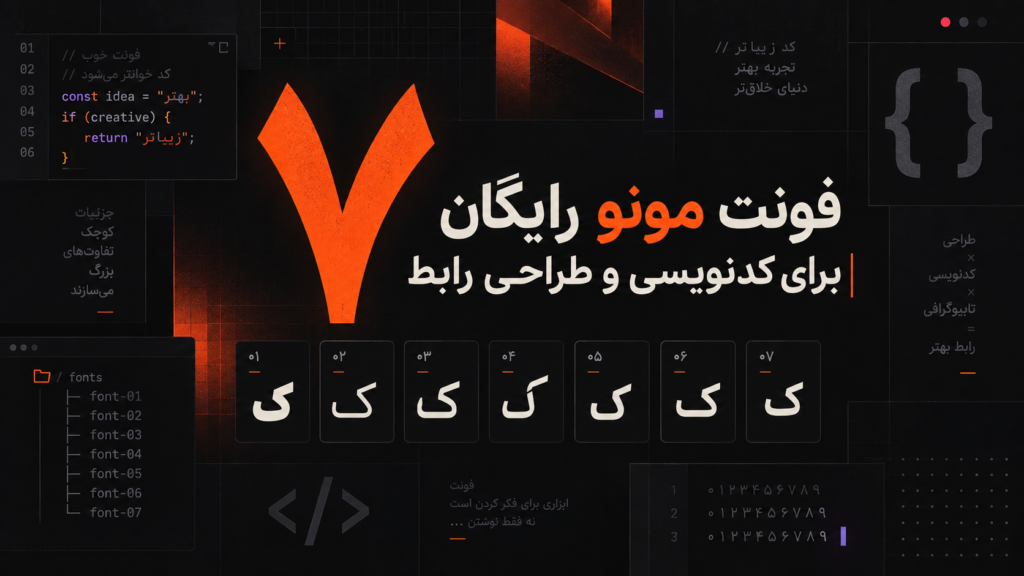
۷ فونت مونو رایگان برای کدنویسی و طراحی رابط
فونت مونو فقط برای نوشتن کد نیست. نظم ثابت حروف در جدول، شماره سفارش، داده‌های مالی و هویت محصولات فنی هم کاربرد دارد. تفاوت اصلی گزینه‌های خوب در تشخیص سریع کاراکترها و خستگی کمتر در استفاده طولانی است.
#چطور این فهرست را انتخاب کردیم؟
تفکیک واضح حروف و اعداد مشابه، تنوع وزن، عملکرد در اندازه کوچک و داشتن شخصیت کافی برای استفاده گرافیکی چهار معیار این فهرست هستند.
#۱. Anonymous Pro
Anonymous Pro فرم آشنا و خوانایی دارد و برای محیط ویرایش کد یا نمونه‌کدهای داخل مقاله انتخابی کم‌حاشیه است.
#۲. Inconsolata
Inconsolata باریک و خوش‌ریتم است؛ در پنجره‌های کدنویسی شلوغ اطلاعات بیشتری را بدون فشردگی آزاردهنده نمایش می‌دهد.
#۳. Monaspace Argon
Monaspace Argon حال‌وهوای مدرن‌تری دارد و برای محصولاتی که رابط فنی بخشی از هویت بصری آن‌هاست جذاب است.
#۴. Fliege Mono
خانواده Fliege با وزن‌های متعدد برای ساخت سلسله‌مراتب در داشبورد، جدول داده و نمونه‌کد انعطاف خوبی فراهم می‌کند.
#۵. Nova Mono
Nova Mono فرمی هندسی و متفاوت دارد و بیشتر برای تیتر کوتاه، عدد و جزئیات گرافیکی فنی پیشنهاد می‌شود.
#۶. Oxanium
Oxanium مرز میان فونت مونو و فونت نمایشی آینده‌نگر را دارد؛ برای بازی، فناوری و رابط‌های مفهومی مناسب است.
#۷. Tektur
Tektur با گوشه‌های صنعتی برای عدد، برچسب و تیتر در داشبوردهای تکنولوژی حضور بصری مشخصی ایجاد می‌کند.